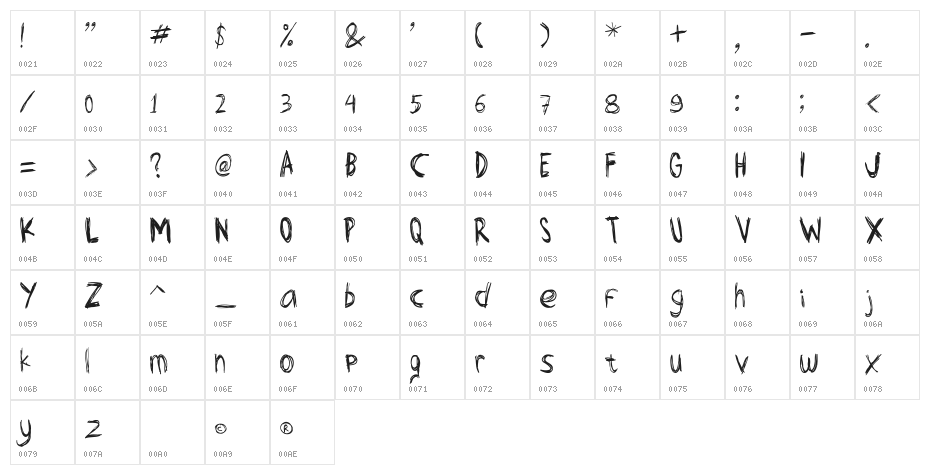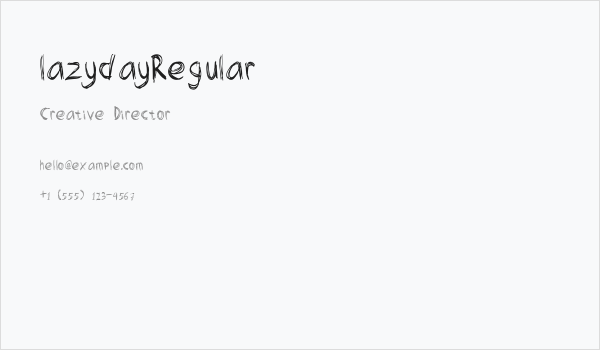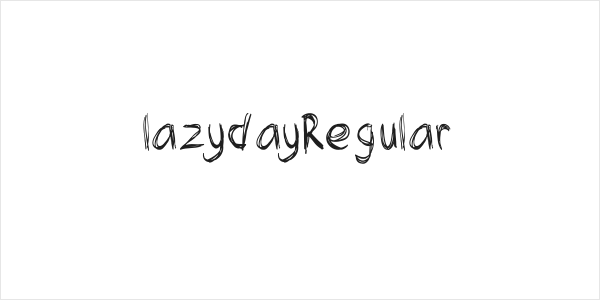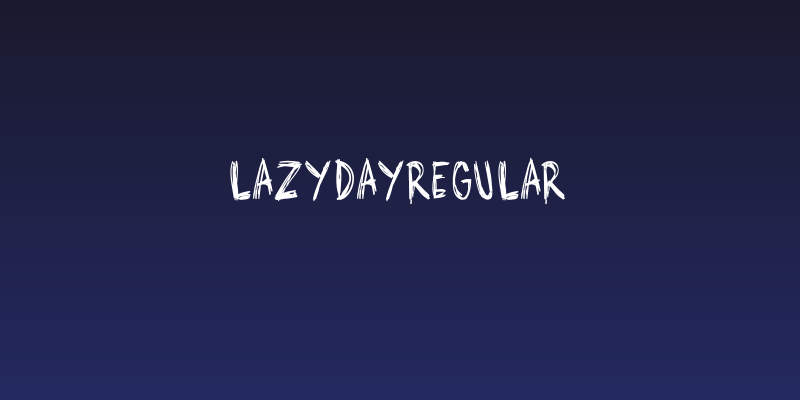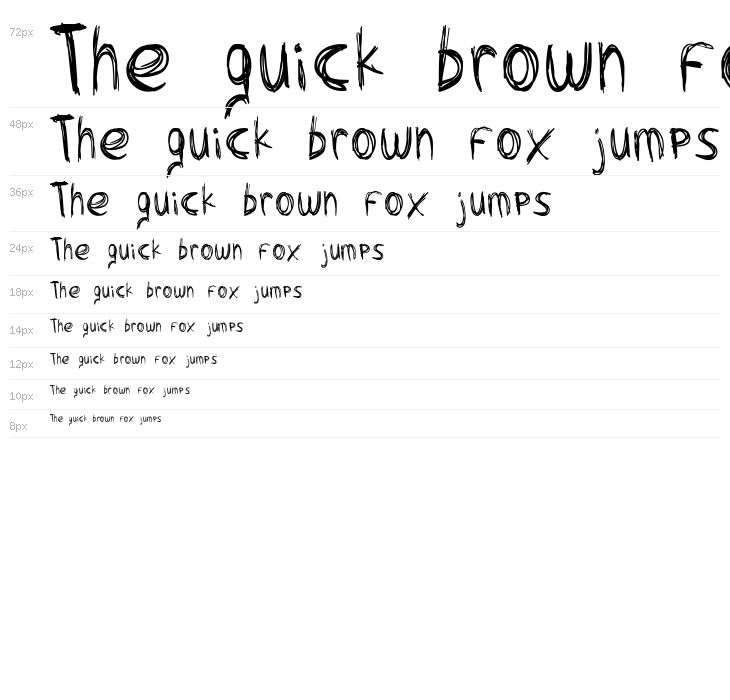
lazydayRegular Font
| Estilo general | Casual, Artistic |
| Caso de uso | Headlines, Posters, Creative Projects |
| Proyectos propuestos | Ideal for children's books, creative posters, casual branding, and artistic invitations. |